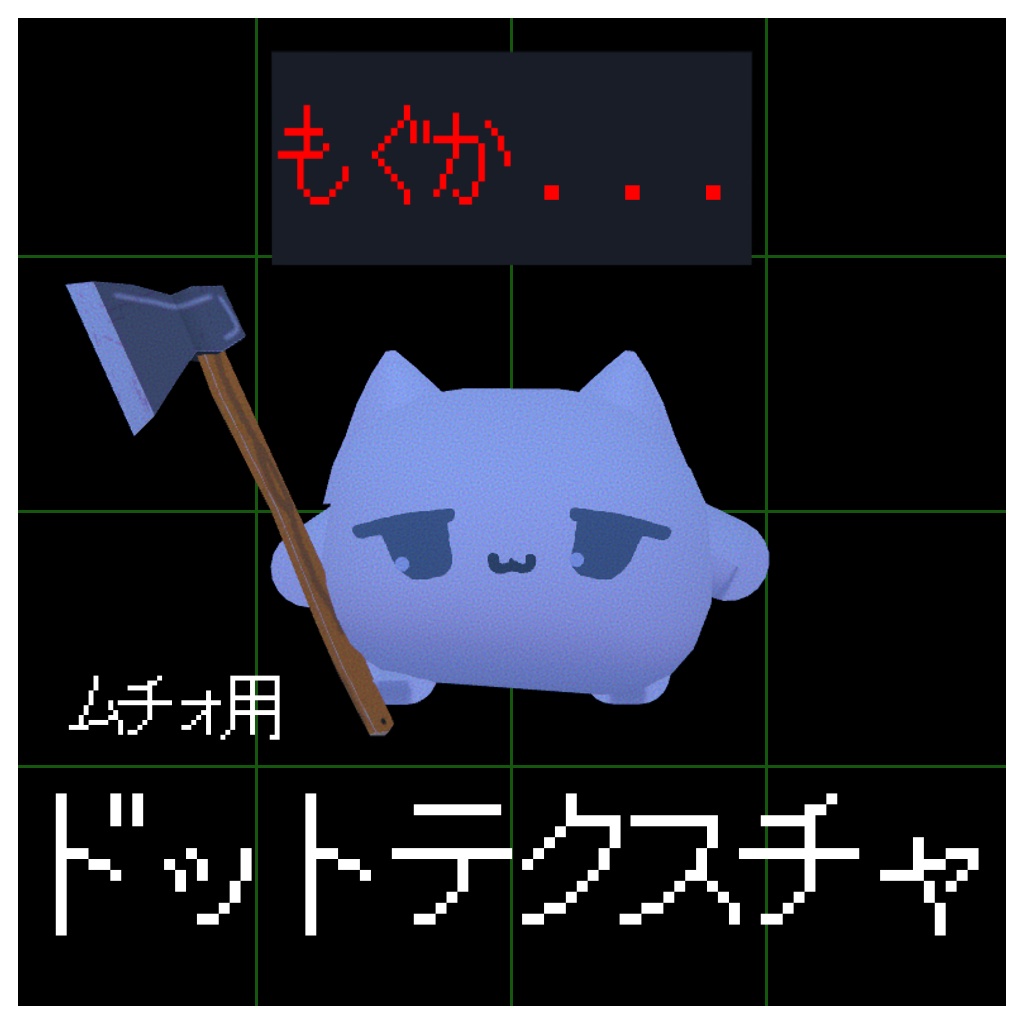
げぼたんマート【ムチォ用】ドットフォントテクスチャ―Digital100 JPY加入购物车Buy a GiftAbout Gift【言葉をおぼえる】なんかしゃべるペット?「ムチォ」【MA対応】 https://booth.pm/ja/items/8657397 のテキストをドットの文字に置き換えるテクスチャ―が6色+3色入ったセットです。 ムチォ本体や、斧は付属しません。 フォントはパブリックドメインのJFドット東雲ゴシック14を使用させていただいております。 2026/8/4 公開 2026/8/6テクスチャを3色追加しました。 げぼたんマート3D Accessories【VRChat】死角げぼたんマート300 JPY3D Textures【Lapwing用】棘まつげメイクテクスチャげぼたんマート300 JPY~3D Clothing【あのめあ用】デフォルト衣装チャイナ化セット ちゃいなめあ🥟げぼたんマート300 JPY